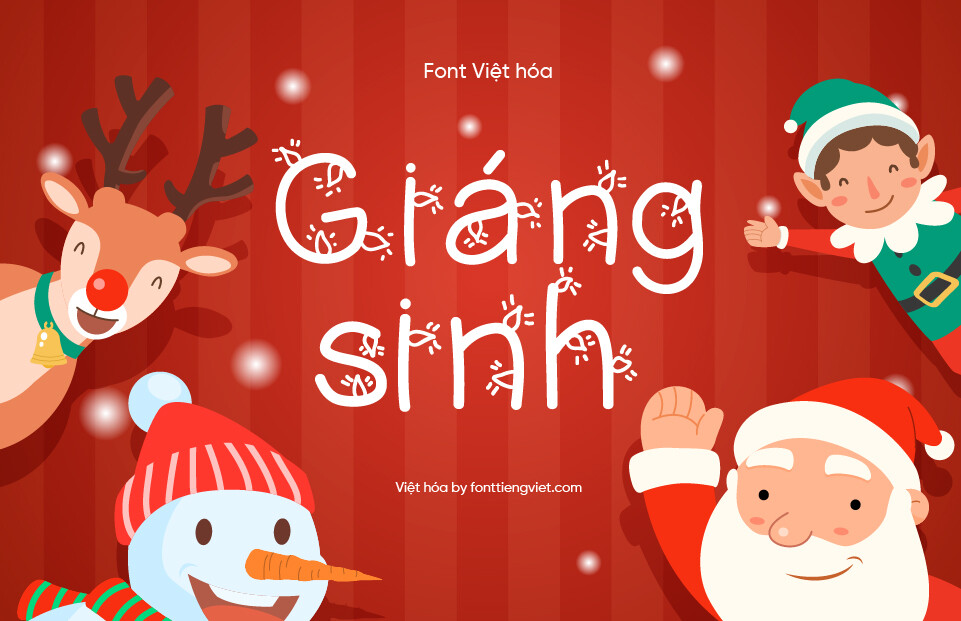
Font Việt hóa 1FTV Christmas Ligtness – Giáng sinh: Font Noel rực rỡ cho thiết kế mùa lễ hội
Mùa Giáng sinh là thời điểm vàng để làm mới hình ảnh thương hiệu, trang trí kênh bán hàng và tạo những ấn phẩm truyền thông ấm áp. Nếu bạn đang tìm một kiểu chữ vừa nổi bật, vừa hỗ trợ tiếng Việt đầy đủ để thiết kế nhanh – đẹp, thì Font Việt hóa 1FTV Christmas Ligtness – Giáng sinh là lựa chọn rất đáng thử. Đây là font trang trí mang tinh thần Noel rõ rệt, phù hợp cho nhiều nhu cầu từ thiết kế cá nhân đến thương mại.
1FTV Christmas Ligtness là gì?
1FTV Christmas Ligtness là font chữ trang trí theo chủ đề Giáng sinh, thường có nét chữ mềm mại, vui tươi và tạo cảm giác “lấp lánh” như ánh đèn Noel. Điểm cộng lớn của phiên bản Việt hóa là hiển thị dấu tiếng Việt ổn định, giúp bạn gõ trực tiếp trong Photoshop, Illustrator, Canva (tùy hệ) hoặc các phần mềm soạn thảo mà không cần chỉnh sửa thủ công quá nhiều.
Ứng dụng thực tế của Font Giáng sinh Việt hóa
Với phong cách đặc trưng mùa lễ hội, font này rất hợp cho các dự án cần tạo không khí ấm áp, rộn ràng:
- Thiết kế poster Noel, banner khuyến mãi cuối năm, standee cửa hàng.
- Làm thiệp chúc mừng Giáng sinh, card quà tặng, tag treo cây thông.
- Thiết kế bìa Facebook, ảnh bìa YouTube, thumbnail video chủ đề Noel.
- Trang trí chữ cho menu quán cà phê, lịch sự kiện, backdrop chụp ảnh.
Ưu điểm nổi bật của Font Việt hóa 1FTV Christmas Ligtness
- Hỗ trợ tiếng Việt: gõ dấu thuận tiện, hạn chế lỗi hiển thị khi dàn trang.
- Đậm chất Noel: giúp tác phẩm “ra vibe” Giáng sinh ngay từ tiêu đề.
- Dễ phối: hợp với font sans/serif tối giản để tạo tương phản đẹp mắt.
- Phù hợp nhiều kích thước: dùng tốt cho tiêu đề lớn, câu chúc ngắn, điểm nhấn.